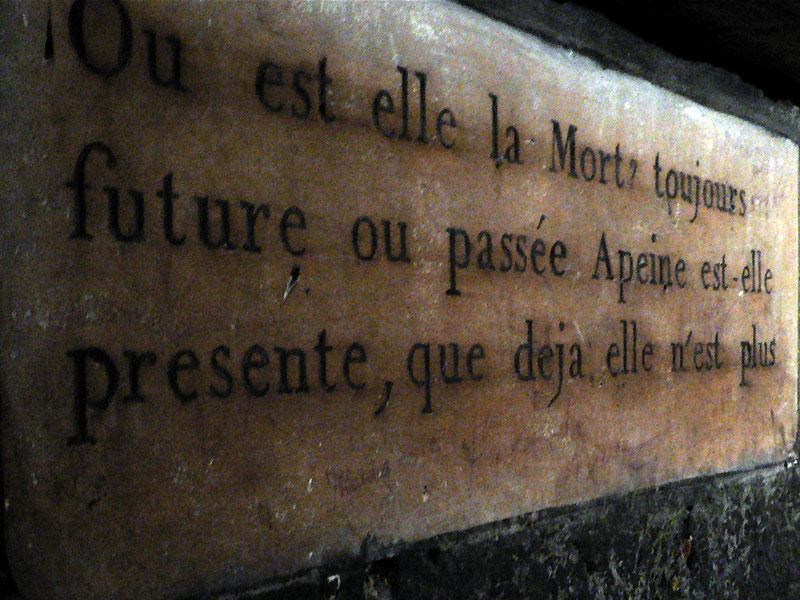
«Kapitälchenfragezeichen»
Gerade beim Aufräumen von alten Fotos gefunden: Ein Fragezeichen auf x-Höhe. (Das ist aus den Pariser Katakomben, Inschrift vermutlich aus dem 19. Jahrhundert.)
Kennt das jemand: Macht «man» das dort so, oder hat man es mal gemacht …? Oder hatte da wohl bloß ein einzelner Steinbildhauer einen lustigen Einfall? Ich finde es ja ganz witzig, bloß siehts von den Proportionen her irgendwie nach «falschem Kapitälchen» aus.
Mmh, ich hab das auch schon bei Druckschriften gesehen, ich komm bloß grad nicht drauf, wo.
Bei der Quadraat SC ist das so, kann man in OT einfach mit den normalen Gemeinen nutzen.
Interessant! Hab ich grad ausprobiert im Font-Tester, sieht ja eigentümlich aus. Als wäre das Fragezeichen runterskaliert … das dann noch im gemischten Satz ist echt ungewohnt :o
Hmmm... ich habe bei der Canapé diese Ersetzungsregel getroffen:
"Smallcaps" (SMCP) --> Fragezeichen bleibt normal, das sähe seltsam/ungewohnt aus.
"All Smallcaps" (SMCP + C2SC) --> Fragezeichen erhält Kapitälchen-Proportionen.
Das sieht dann harmonischer aus als mit Versalhöhe. (Allerdings habe ich dann auch Kapitälchenziffern ... :rockon: )
Macht Sinn. :cheer:
So ein Kapitälchenzeichen im gemischten Satz sieht schon eigen aus … wäre doch schön, man könnte so Inschriften fragen, warum sie so herausgekommen sind, wie sie eben sind. :)